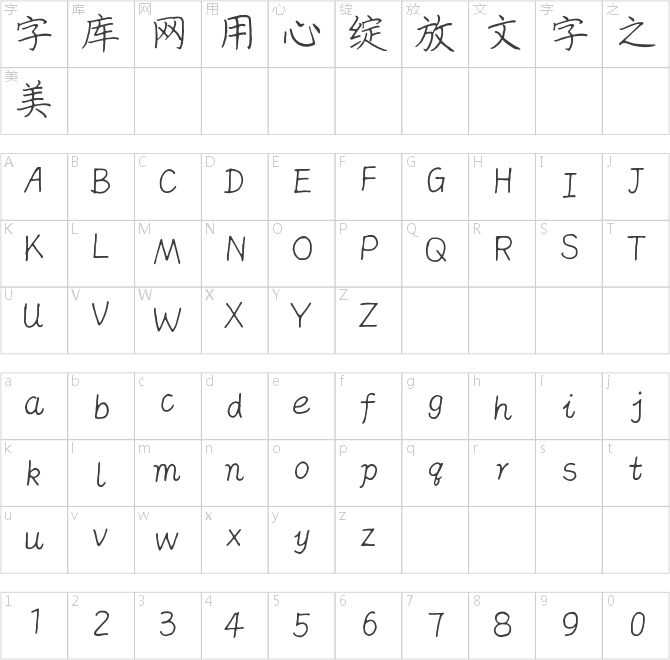
倉(cāng)耳曹哲斌楷書
倉(cāng)耳字庫(kù)
楷書
倉(cāng)耳曹哲斌楷書簡(jiǎn)繁字體字庫(kù)是一款讓人賞心悅目、百看不厭的中文字體,適合各類廣告和產(chǎn)品包裝設(shè)計(jì)應(yīng)用,字體大小11.82MB,格式為ttf字體,上傳用戶是373790005,作者/版權(quán)方為倉(cāng)耳字庫(kù)